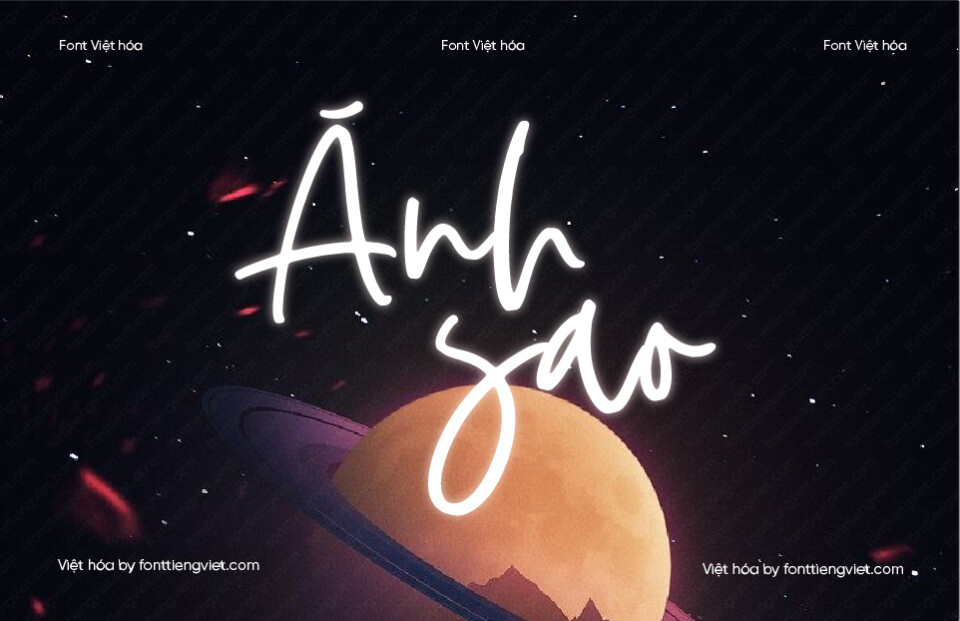
Tải Ngay Font Việt hóa 1FTV VIP Austone Winter – Đỉnh Cao Sáng Tạo Cho Thiết Kế Chữ Viết Tay
Khám phá vẻ đẹp cuốn hút của Font Việt hóa 1FTV VIP Austone Winter
Trong thế giới đồ họa hiện đại, việc lựa chọn một Font Chữ phù hợp đóng vai trò quyết định đến cảm xúc của người xem. Font Việt hóa 1FTV VIP Austone Winter là một tác phẩm nghệ thuật thuộc phong cách Script với những đường nét uốn lượn mềm mại và thanh thoát. Bộ font này không chỉ mang lại cảm giác ấm áp của mùa đông mà còn thể hiện sự tinh tế, sang trọng trong từng ký tự. Nhờ quá trình việt hóa chỉn chu, người dùng tại Việt Nam có thể dễ dàng sử dụng các dấu câu mà không lo lỗi hiển thị.
Đặc điểm nổi bật và tính ứng dụng linh hoạt
Font Việt hóa 1FTV VIP Austone Winter sở hữu các đường nối chữ (ligatures) tự nhiên, tạo cảm giác như nét vẽ tay thực thụ. Đây là lựa chọn lý tưởng cho các bạn học sinh, sinh viên khi thực hiện các dự án thiết kế thiệp chúc mừng, bìa sách hay các bài thuyết trình đầy tính nghệ thuật. Ngoài ra, các nhà thiết kế chuyên nghiệp thường ưu tiên bộ font này cho các dự án nhận diện thương hiệu, thiết kế logo và các ấn phẩm truyền thông mạng xã hội yêu cầu sự độc đáo và phá cách.